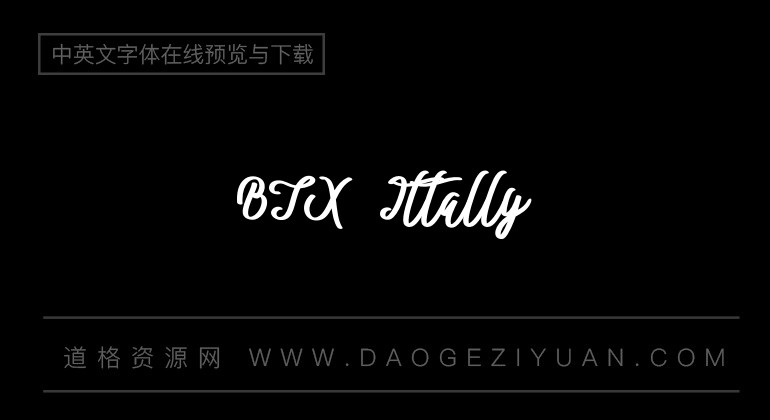
BTX Ittally
BTX Ittally是一种现代风格的字体,由设计师Brian Kent创造。它具有一种自然的流畅感和独特的笔画形状,可用于很多不同的设计项目。 BTX Ittally字体拥有多种字重和风格,包括粗体、斜体、轻体和黑体等,因此可以用于各种场合,例如海报、标志、包装设计、书籍设计等等。此外,该字体还支持多种语言,因此您可以使用它来设计各种多语言项目。 总的来说,BTX Ittally是一款具有独特特点的现代字体,可以为您的设计项目增添一分独特的风格。
BTX Ittally是一款非常不错的手写艺术字体,具有很好的视觉感,适合于文化类的宣传设计、商业类品牌的广告和产品包装设计以及个性化文字排版等较多场景。